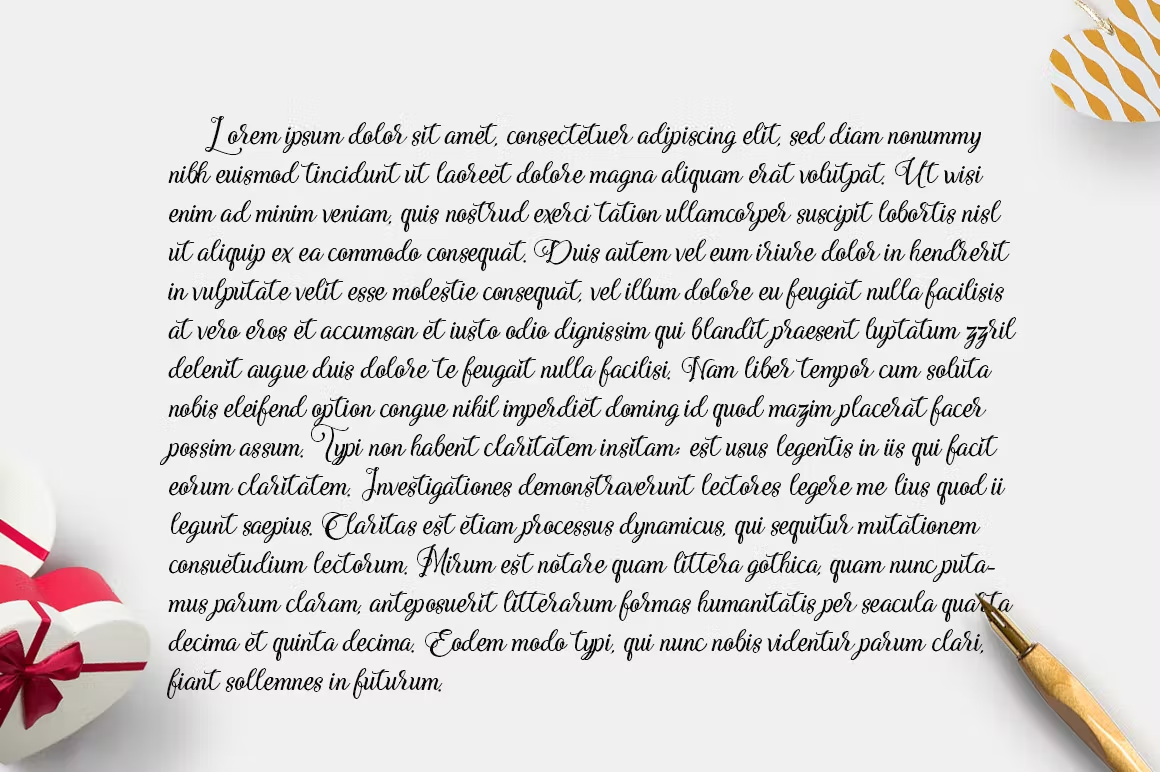
Adorabelle Elegant Wdding Font
Description de Adorabelle Elegant Wdding Font
Adorabelle Script – une nouvelle écriture fraîche et moderne avec un style calligraphique, des personnages décoratifs et une ligne de base dansante ! Tellement beau sur invitation comme des cartes de vœux, du matériel de marque, des cartes de visite, des citations, des affiches et bien plus encore !
Adorabelle est livrée avec 500 glyphes supplémentaires. Les caractères alternatifs ont été divisés en plusieurs fonctionnalités de type ouvert telles que les ensembles stylistiques, les alternatives stylistiques, l’alternative contextuelle, SWASH et la ligature. Les fonctionnalités d’Open Type sont accessibles à l’aide de programmes avancés d’Open Type tels qu’Adobe Illustrator, Adobe InDesign, Adobe Photoshop Corel Draw X version et Microsoft Word. Et cette police a donné PUA unicode (polices spécialement codées). afin que tous les personnages alternatifs soient facilement accessibles dans leur intégralité par un artisan ou un designer
Caractéristiques :
Suppléants initiaux
Alternatives aux terminaux
Ligatures standards
Ligatures uniques
Alternatives stylistiques
Ensembles stylistiques
Alternatives contextuelles
SWASH
Latin de base A-Z et a-z
Nombres
Les symboles internationaux incluent